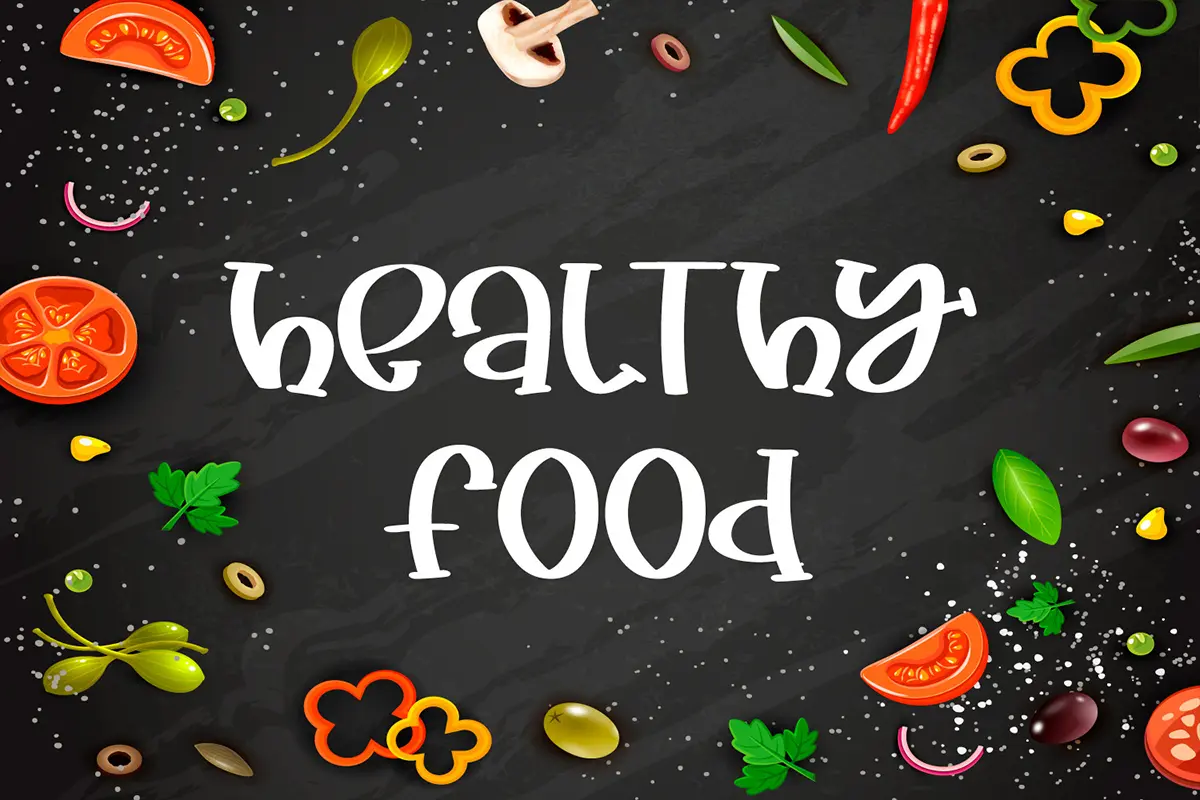
فونت نمایشی بامزه و مدرن
فونت Tasty Food یک فونت نمایشی (Display Font) با طراحی شاد، بامزه و پرانرژی است که حس بازیگوشی و جذابیت را به نوشتههای شما اضافه میکند. این فونت با سبک پرشدار و دلنشین خود، انتخابی عالی برای پروژههایی است که نیاز به لمس کودکانه، غیررسمی و خلاقانه دارند.
⭐ ویژگیهای محصول
- سبک: فونت نمایشی شاد و مدرن
- طراحی پرشدار، بامزه و دلنشین
- ایدهآل برای افزودن حس سرگرمی و خلاقیت به کارها
🎯 موارد استفاده
- طراحی پوسترهای کودکانه و سرگرمی
- ساخت بازیها و پروژههای آموزشی برای کودکان
- استفاده در کارتهای تبریک و دعوتنامههای دوستانه
- افزودن به پورتفولیو طراحان برای نمایش سبکهای شاد و غیررسمی